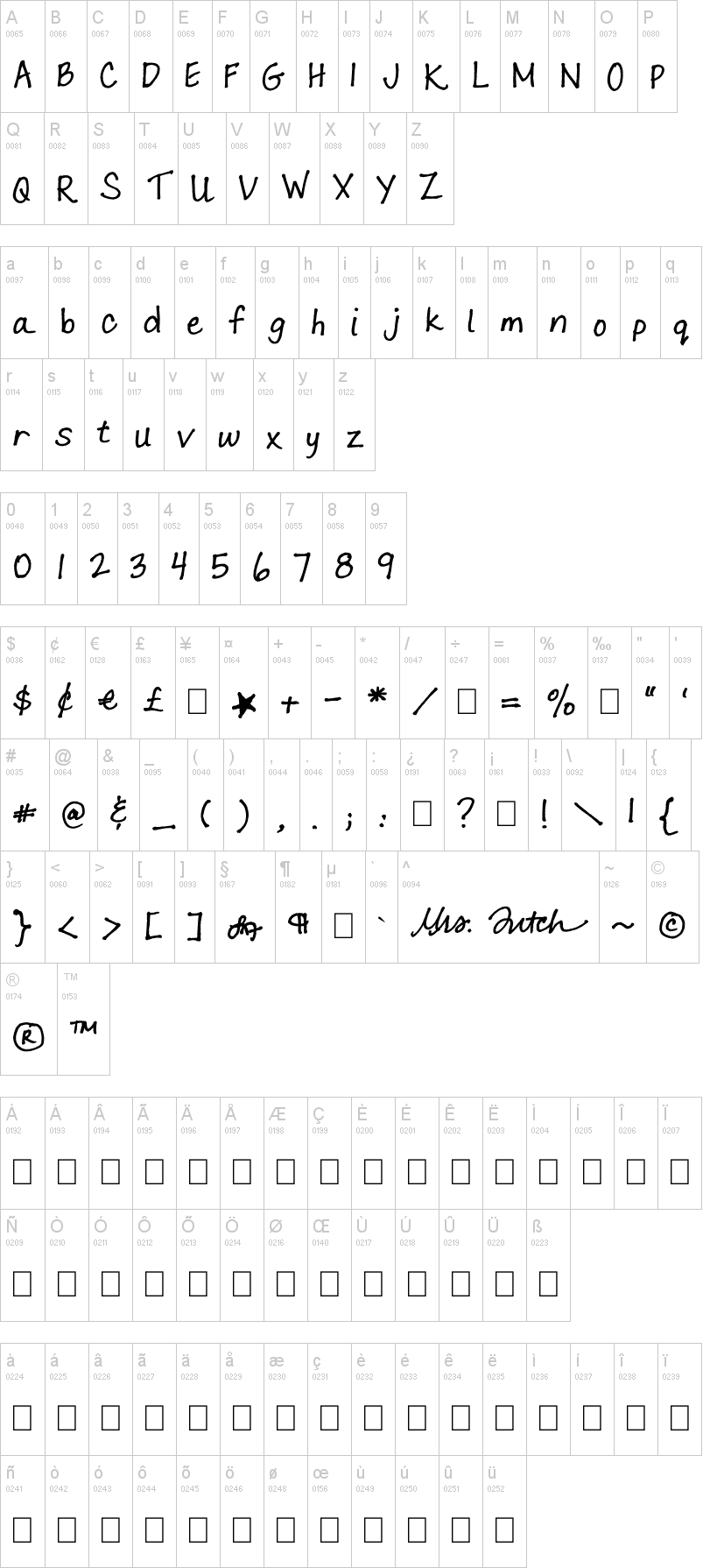
Lara Prints
Lara Prints 是一种手写风格的字体,具有温暖、自然、舒适的感觉。该字体采用了不规则的手写笔画,字母与字母之间的距离较近,让文本看起来更加自然流畅。Lara Prints 字体适用于各种印刷和数字设计项目,例如海报、名片、包装、标志、网站和社交媒体图形等。它适合许多不同类型的项目,从时尚和美容到食品和旅游。Lara Prints 字体还提供了多种形式和变化,如粗体、斜体和阴影版本,以满足不同设计需求。
Lara Prints是一款非常不错的手写艺术字体,具有很好的视觉感,适合于文化类的宣传设计、商业类品牌的广告和产品包装设计以及个性化文字排版等较多场景。
Lara Prints字符映射图